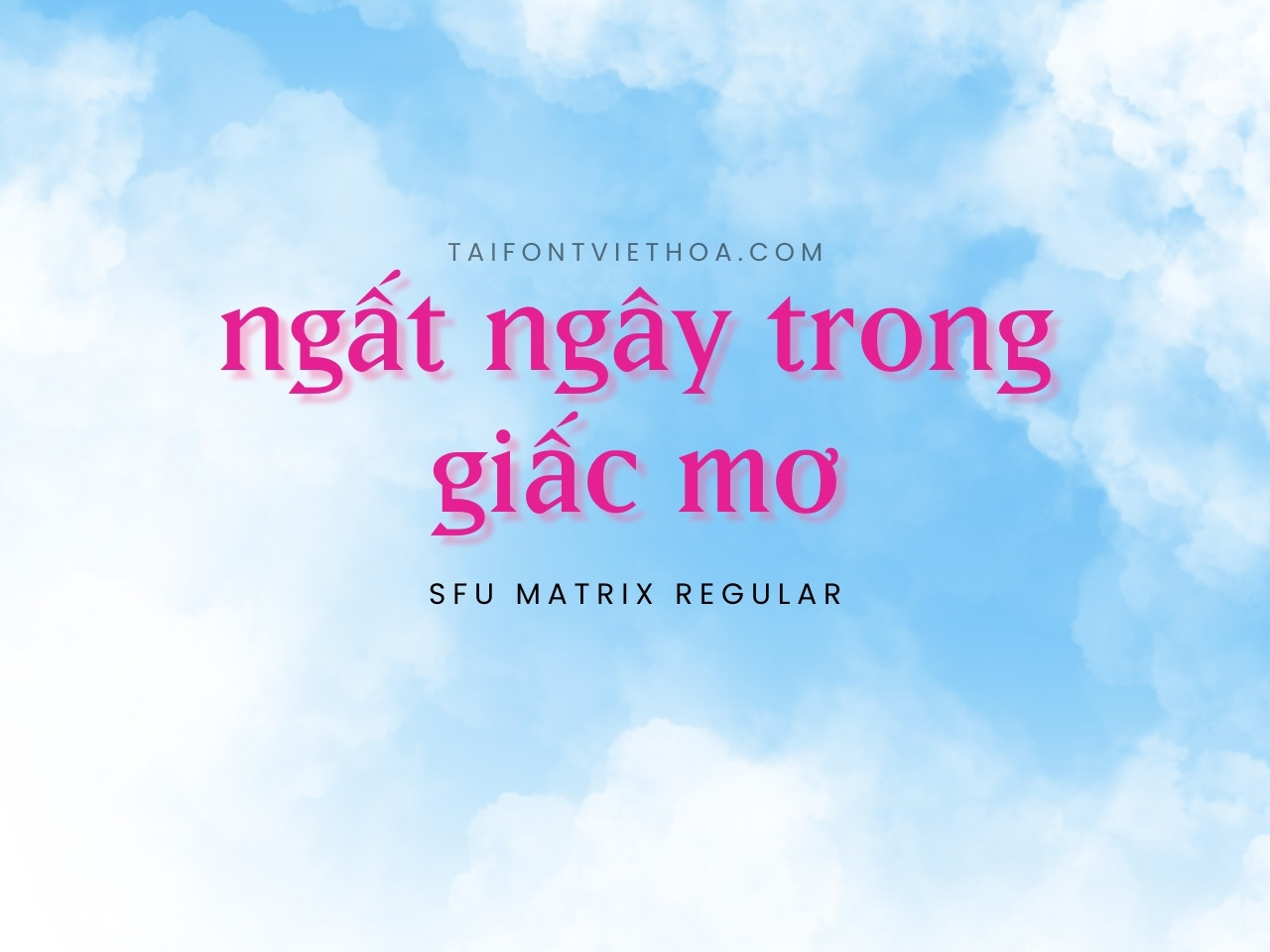
Giới thiệu về SFU Matrix – Phong cách cổ điển, đậm chất máy tính
SFU Matrix là phiên bản Việt hóa của font “Matrix” – một kiểu chữ serif mang hơi hướng retro, được cộng đồng Font Việt Hóa phát triển dựa trên bản gốc từ các nguồn như Font2s.com. Phiên bản Việt hóa SFU Matrix được đăng tải vào tháng 10/2023, hỗ trợ đầy đủ bảng ký tự tiếng Việt chuẩn Unicode và vẫn giữ nguyên tính sắc sảo, góc cạnh đặc trưng của font, phù hợp với các dự án mang phong cách công nghệ, vintage palette.
Bản gốc Matrix hỗ trợ ký tự Latin Extended, do đó ngoài tiếng Việt còn tương thích tốt với các ngôn ngữ Tây Âu như tiếng Anh, Pháp, Đức… giúp dễ dàng ứng dụng cho các thiết kế đa ngôn ngữ.
Đặc điểm thiết kế & ứng dụng ấn tượng
SFU Matrix thuộc dòng serif hiển thị, cấu trúc chữ góc cạnh, định hình vuông vức. Các nét chân nhỏ nhưng rõ, tạo cảm giác mạnh mẽ, gợi nhớ đến phong cách máy tính cổ điển và nghệ thuật ASCII. Độ tương phản giữa nét dày và nét mảnh tạo chiều sâu, giúp tiêu đề hoặc logo dễ nhận diện khi đặt trên nền tối hoặc sáng.
Ứng dụng phù hợp:Thiết kế poster phim, banner quảng cáo theo phong cách vintage/công nghệ, tiêu đề slide, logo startup công nghệ, bộ nhận diện doanh nghiệp, thiết kế áo thun, sản phẩm số hóa.
Ngành nghề phù hợp:Công nghệ – IT, truyền thông – quảng cáo, thiết kế đồ họa, sản xuất/máy móc công nghiệp, ngành game – giải trí, startup – thương hiệu kỹ thuật số.